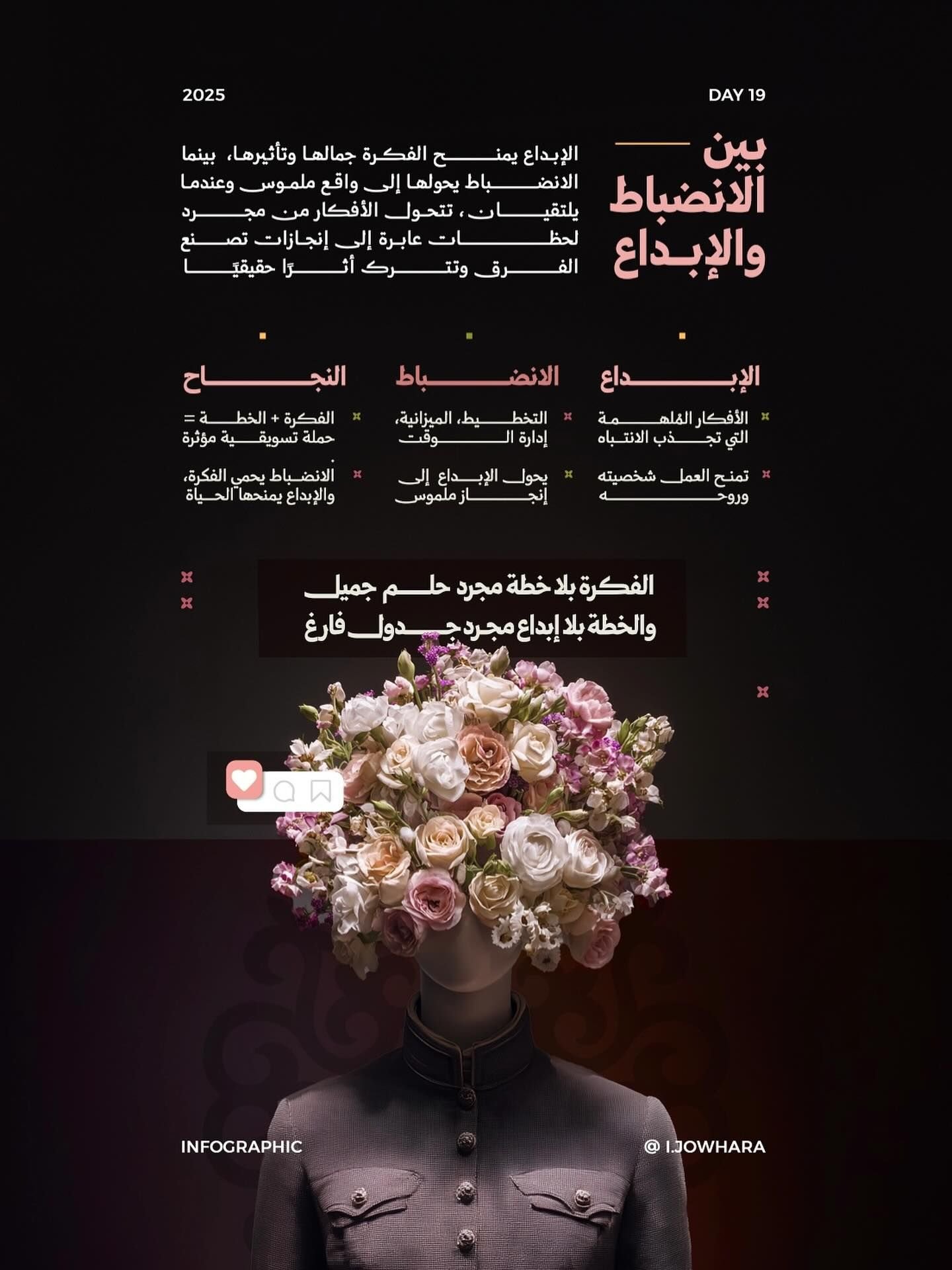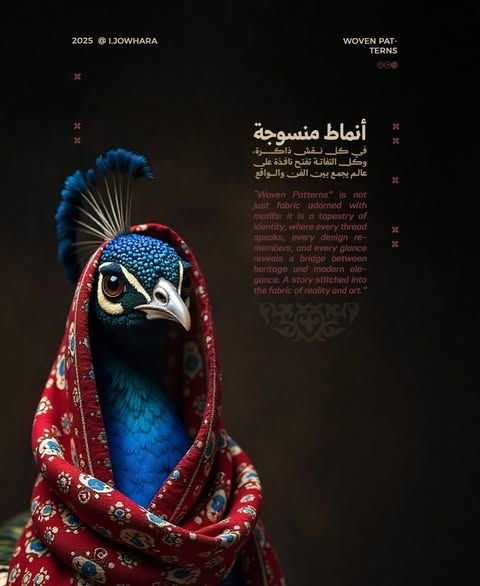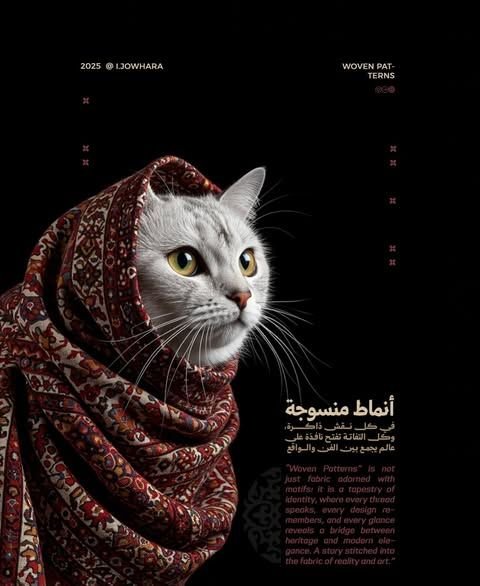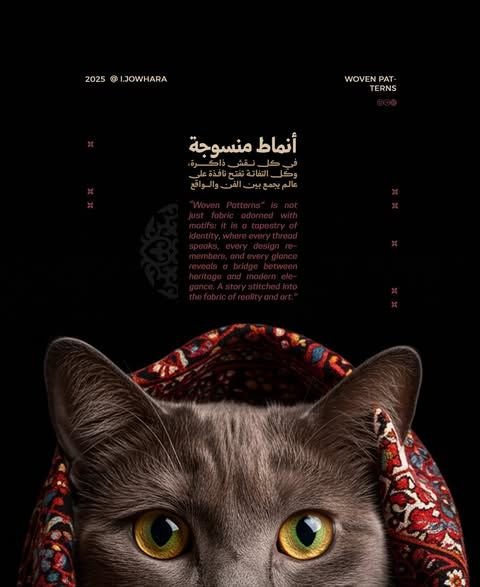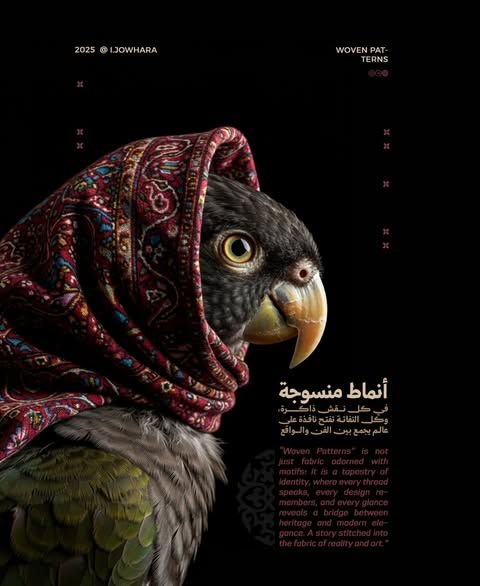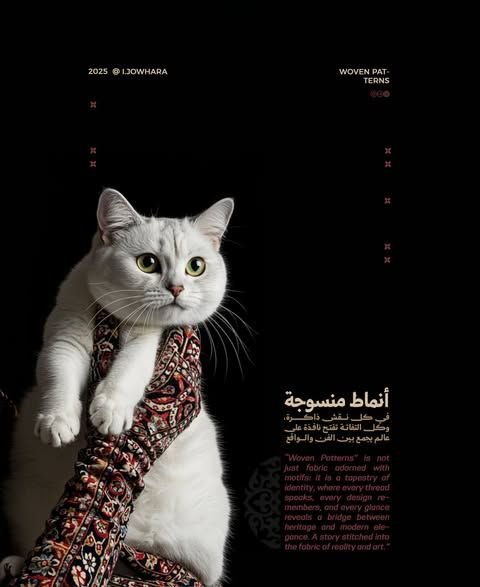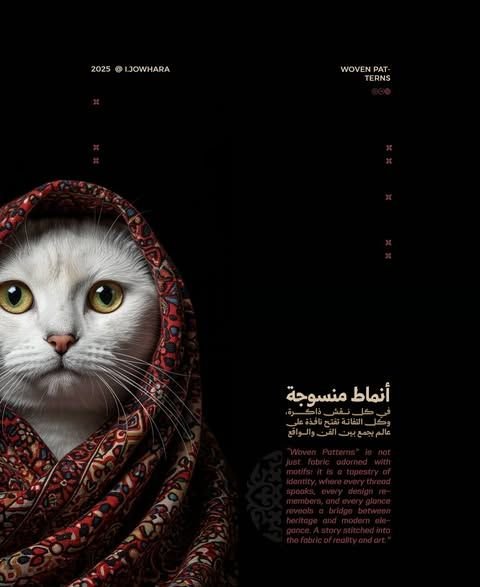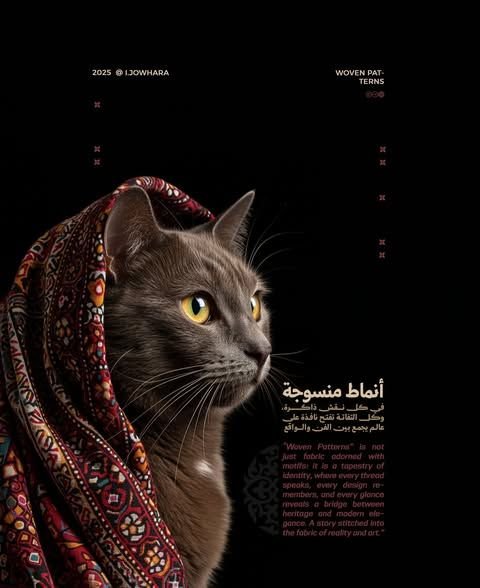
خط وثيق في أعمال جوهرة — خط نسخ عربي
خط وثيق خط عربي–لاتيني مستوحى من النسخ مع لمسات من الثلث، يتميز بحروف قوية وتجويفات ضيقة تجعله مثاليًا للعناوين، الأخبار، والشعارات. يتوفر في سبعة أوزان متدرجة لمرونة أكبر في التصميم.